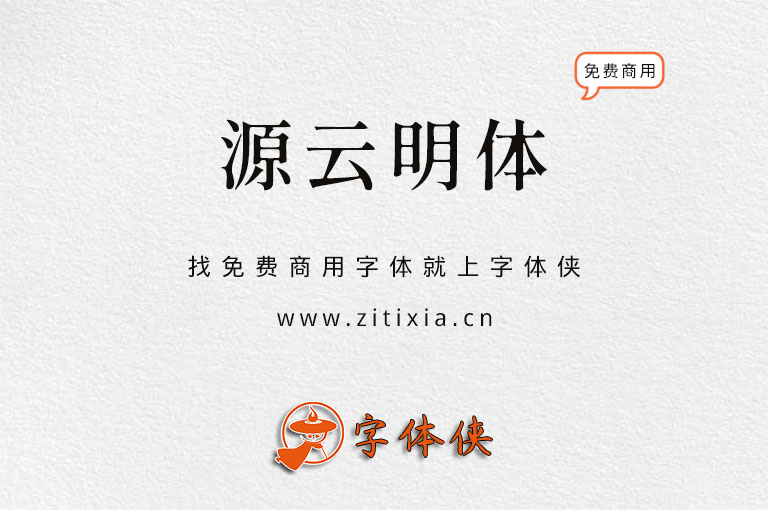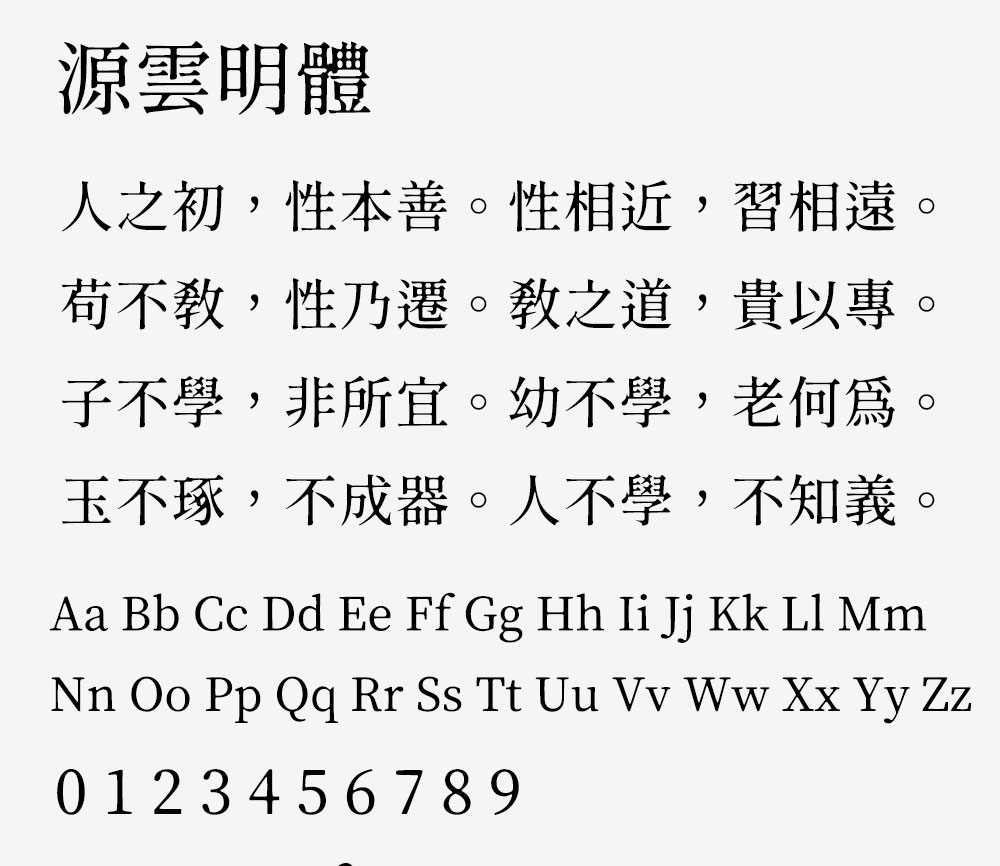
台湾最活跃的字型社团「字嗨」管理员 But Ko 释出三款改造自思源宋体的繁体中文字型,开放让需要的使用者免费下载!分别为:源样明体、源流明体及源云明体,不过目前仍在公测阶段,不排除未来有大幅更改规格的可能性。无论如何,可以从 GitHub 页面下载使用,将测试结果反映给开发者。
源云明体-Light,「源云明体」是基于 「 思源宋体 」 的而改造的开放原始码中文字型。「源云明体」在横笔的起笔及竖笔的起笔、收笔处加入粗细变化,笔画交叉处有朦胧处理,使字体怀旧而带点感性。该字形提供Light、Regular、Medium、SemiBold等4个字重,能广泛运用在多种情境。字型改造虽以电脑程序自动进行,但在一些细节调整后可以明显感受出不同效果。
「源云明体」保留「思源宋体」所支持之所有汉字(包或日、韩文汉字与简体字),一般会用到的汉字几乎不会有缺字问题。 同时也保留了所有日文假名。(但删除了高达1万字的韩文字,有效降低字体文档的大小)